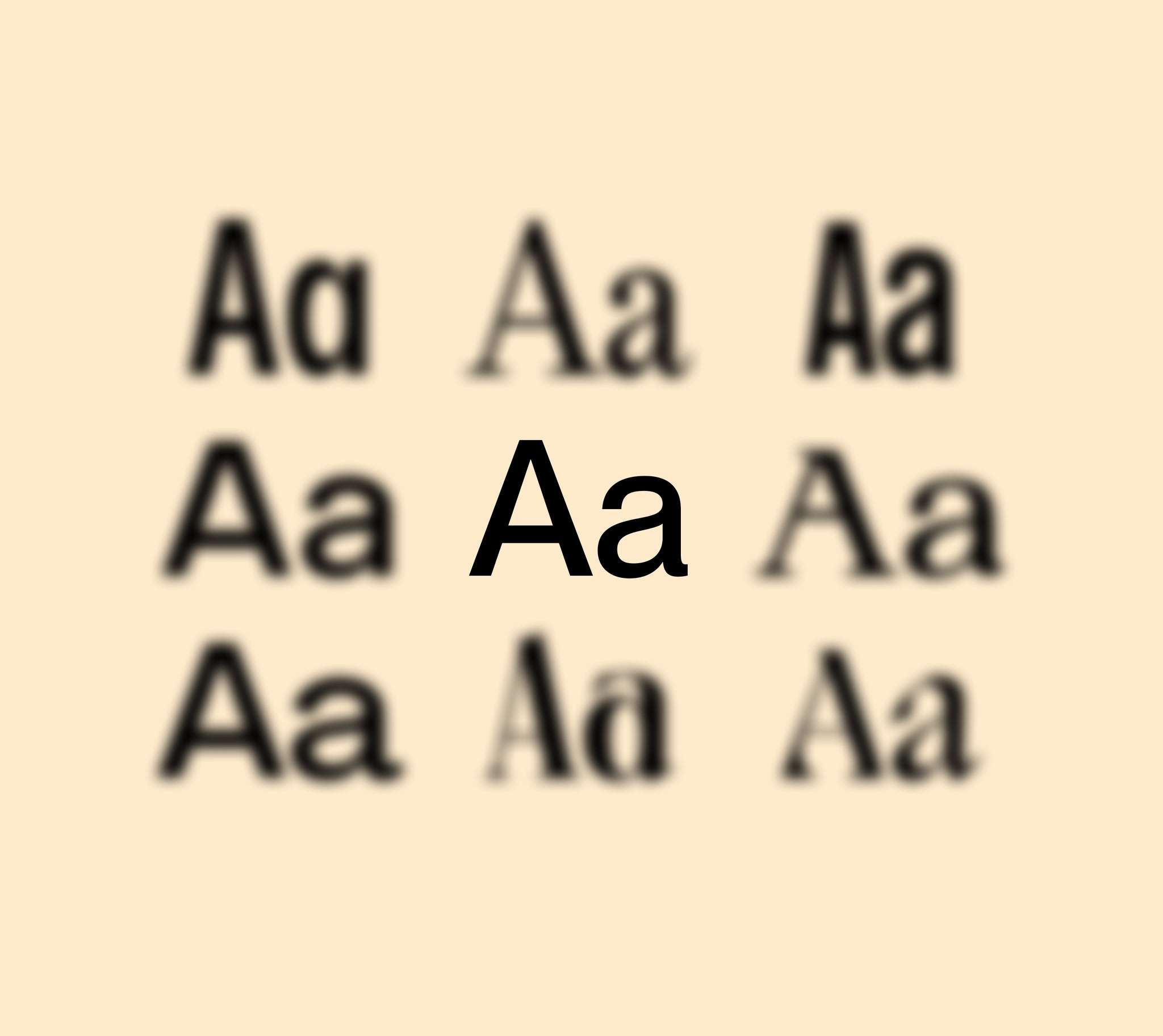
L'une des compétences les plus importantes à acquérir en tant que designer est le choix de la typographie. En effet, le texte est l'un des principaux s de communication des designers avec les utilisateurs. La typographie peut faire la différence entre un design et son échec.
La typographie est à la fois belle et complexe. Certaines personnes y consacrent toute leur carrière. Heureusement, leur travail est bien documenté, ce qui nous permet de disposer de nombreuses ressources en ligne sur la typographie.
Cet article est conçu pour vous aider à choisir la typographie de vos créations. Il vous encouragera à explorer des polices et des combinaisons de polices au-delà de celles que vous connaissez déjà.
Un bon design doit aligner sa typographie sur son objectif. En effet, la typographie est essentielle pour créer l'ambiance, le ton et le style de vos créations.
Par exemple, si vous créez une carte de vœux riche en illustrations, choisissez une police adaptée au style de votre illustration. Harmonisez votre typographie avec le reste de votre design.
Si vous concevez une page de destination axée sur les images, choisissez une police simple qui ne détourne pas l'attention de vos images. Utilisez la typographie pour mettre en valeur les informations et communiquer du sens.
Identifiez votre public
Après avoir déterminé l'objectif de votre design, identifiez votre public. Cette étape est cruciale, car l'âge et les centres d'intérêt influenceront vos choix de polices.
Après avoir clarifié l'objectif de votre design, identifiez votre public. Cette étape est cruciale, car des informations sur vos utilisateurs, telles que leur âge, leurs centres d'intérêt et leur éducation culturelle, peuvent influencer vos choix en fonction de votre type de public.
Par exemple, certaines polices sont plus adaptées aux enfants. Pour apprendre à lire, les enfants ont besoin de polices très lisibles avec des lettres généreuses. Sassoon Primary en est un bon exemple. Développée par Rosemary Sassoon , Sassoon Primary s'appuie sur ses recherches pour identifier les types de lettres faciles à lire pour les enfants.
D'autres polices sont plus adaptées aux seniors. Les polices adaptées aux seniors utilisent des tailles lisibles, des couleurs très contrastées et évitent les scripts et les styles décoratifs.
Lors du choix du type de contenu, tenez compte de votre public et de ses besoins. En bref, faites preuve d'empathie envers vos utilisateurs.
Cherchez l'inspiration
Observez le travail d'autres designers. Essayez de comprendre comment ils ont choisi leur typographie.
Inspiration de police
Pour vous inspirer en matière de polices, consultez l'article « Les 100 meilleures polices gratuites » de CreativeBloq, qui vous aidera à choisir la police idéale. CreativeBloq y explique les motivations derrière chaque police.
Une autre ressource utile est la collection des 100 meilleures polices gratuites de 2015 d'Awwwards. Invision a également compilé un vaste répertoire de ressources typographiques . Vous y trouverez de nombreuses sources d'inspiration.
Pour vous inspirer de sites web réels, consultez Typ.io. Le site sélectionne des polices inspirées du web. De plus, il fournit des définitions de polices CSS au bas de chaque exemple d'inspiration.
Outre les sites web dédiés à l'inspiration en matière de polices, visitez vos sites préférés et découvrez les polices qu'ils utilisent. WhatTheFont est un excellent outil pour cela. WhatTheFont est une extension Chrome qui vous permet d'inspecter les polices web en les survolant.
Inspiration d'appariement
Au-delà des polices, inspirez-vous également de l'association des polices. L'association des polices est tout aussi importante que les polices elles-mêmes. Une bonne association de polices permet d'établir une hiérarchie visuelle et d'améliorer la lisibilité de vos créations.
Pour trouver l'inspiration, commencez par Typewolf . Typewolf sélectionne des idées d'association de polices sur différents sites. Ils proposent également des recommandations de polices et des guides typographiques détaillés. C'est une mine d'or pour les typographes.
FontPair propose également des idées d'association de polices, notamment pour Google Fonts . Vous pouvez trier par combinaisons de styles de polices, comme sans-serif et serif, ou serif et serif. Pangram a également écrit trois volumes de Typewolf sur l'association de polices.
Enfin, il existe de nombreuses collections d'associations de polices créées par des designers en ligne. Par exemple , Pangram Free Font Pairing Guide — Vol. 1 , Typography:Google Fonts Combinations et Typography: Google Fonts Combinations Volume 2. Il suffit de rechercher « association de polices » sur des sites comme Behance et Dribbble .
Choisissez vos polices
Fort de vos recherches et de votre inspiration, vous êtes prêt à choisir votre police. Pour ce faire, gardez à l'esprit les principes suivants : lisibilité, lisibilité et finalité.
Choisissez des polices classiques et faciles à lire. Évitez les polices trop décoratives et privilégiez des polices simples et pratiques. Soyez également attentif à l'usage que vous en ferez. Par exemple, certaines polices sont plus adaptées aux en-têtes qu'au corps du texte.
Pour cette raison, avant de choisir une police, recherchez son objectif.
En matière d'association de polices, privilégiez la simplicité avec un maximum de trois polices différentes. Associez également des polices contrastées. Cela permettra de guider le regard des lecteurs, d'abord vers les titres, puis vers le corps du texte. Vous pouvez également créer un contraste visuel en utilisant différentes tailles, couleurs et graisses de police.
Pour les polices web, vous pouvez utiliser Pangram , Google Fonts , Typekit et Font Squirrel . Les polices Pangram Pangram® sont gratuites pour un usage personnel, Google Fonts est gratuit, et Typekit et Font Squirrel proposent des polices gratuites et payantes.
Déterminer les tailles de police
Après avoir choisi une combinaison de polices, l'étape suivante consiste à déterminer la taille. Modular Scale, de Tim Brown , responsable typographie chez Adobe, est un excellent outil pour cela. Modular Scale est un système permettant d'identifier des ratios historiquement satisfaisants afin de créer des échelles permettant de déterminer la taille des caractères.
Par exemple, vous pourriez utiliser une échelle basée sur le nombre d'or. Voici vos cinq premières options de taille de police calculée :
Nombre d'or (1:1,618) 1,000 x 1,618 = 1,618 1,618 x 1,618 = 2,618 2,618 x 1,618 = 4,236 4,236 x 1,618 = 6,854 6,854 x 1,618 = 11,089
Un problème que vous pourriez rencontrer est que votre rapport est trop grand. Observez ce qui arrive aux derniers intervalles de notre échelle en fonction du nombre d'or.
Nombre d'or (1:1,618) ... 11,089 x 1,618 = 17,942 17,942 x 1,618 = 29,03 29,030 x 1,618 = 46,971 46,971 x 1,618 = 75,999 75,999 x 1,618 = 122,966
Comme vous pouvez le constater, les intervalles entre les nombres deviennent trop grands. La plupart des interfaces nécessitent des intervalles plus petits. Heureusement, Modular Scale propose une variété de ratios basés sur la géométrie, la nature et la musique.
Seconde mineure 15:16 Seconde majeure 8:9 Tierce mineure 5:6 Tierce majeure 4:5 ...
Ainsi, au lieu d'utiliser le nombre d'or, vous pouvez utiliser des rapports qui produisent des intervalles plus petits comme la quarte parfaite.
Quarte parfaite (3:4) ... 9,969 x 1,333 = 13,288 13,288 x 1,333 = 17,713 17,713 x 1,333 = 23,612 23,612 x 1,333 = 31,475 31,475 x 1,333 = 41,956 41,956 x 1,333 = 55,927
Une fois que vous avez choisi une échelle, vous pouvez sélectionner les tailles de police dans votre liste et les arrondir à la décimale la plus proche.
Tailles de police En-tête 1 : 55 px En-tête 2 : 42 px En-tête 3 : 31 px En-tête 4 : 24 px En-tête 5 : 14 px Corps : 17 px Légende : 14 px
La méthode d'échelle modulaire utilise une précision mathématique pour générer les tailles de police. Cependant, il ne s'agit que d'une indication. Utilisez cette méthode comme point de départ, puis ajustez les tailles à l'œil nu.
Créer un guide de style typographique
La dernière étape du processus consiste à créer un guide de style pour votre typographie afin de vous aider à standardiser le type dans vos conceptions.
Dans des programmes comme Sketch , vous pouvez créer des styles de texte partagés pour insérer rapidement du texte avec des styles déjà appliqués à partir de votre guide.
C'est au cours de cette étape du processus que vous pouvez peaufiner et finaliser les attributs de votre texte tels que la couleur, le poids et la taille.
Un mot sur la couleur : lorsque vous choisissez une couleur, tenez compte de votre palette de couleurs. Choisissez des couleurs qui correspondent à votre type et qui s'harmonisent avec votre palette.
Utilisez des guides de style pour standardiser le type dans vos conceptions
Dans votre guide de style, assurez-vous d'inclure au moins les éléments suivants : définitions de police, tailles de police, couleurs de police et exemples d'utilisation.
Les directives typographiques Material Design de Google sont un bon exemple de ce qu'il faut inclure dans un guide de style. Parmi les autres exemples, on peut citer les guides typographiques de Mailchimp . , et Focus Labs .
La typographie est une question d'expérimentation. C'est à la fois une science et un art.
Je vous mets au défi de sortir de votre zone de confort et d’explorer le type dans votre conception.